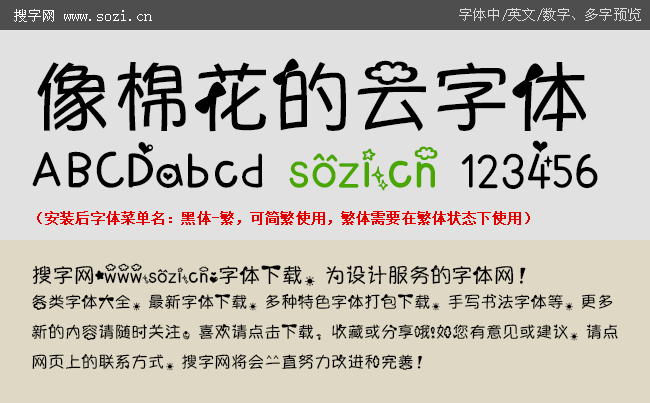
像棉花的云字體
搜字網(wǎng)給大家提供一款很卡通的手機(jī)中文字體下載。修改者給這款字體叫像棉花的云字體,這款手機(jī)中文字體以POP字體為原形,在筆畫間嵌入有趣的卡通圖形,該中文字體趣味性強(qiáng),又保持了文字的識(shí)別度,非常適合喜歡卡通的朋友在手機(jī)上安裝使用。